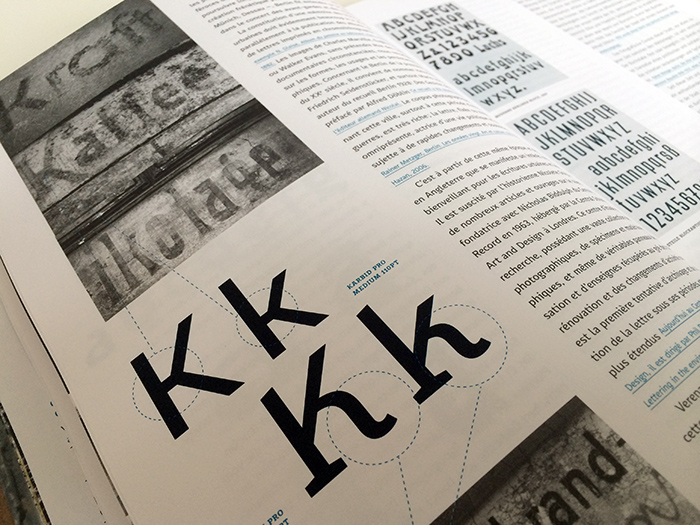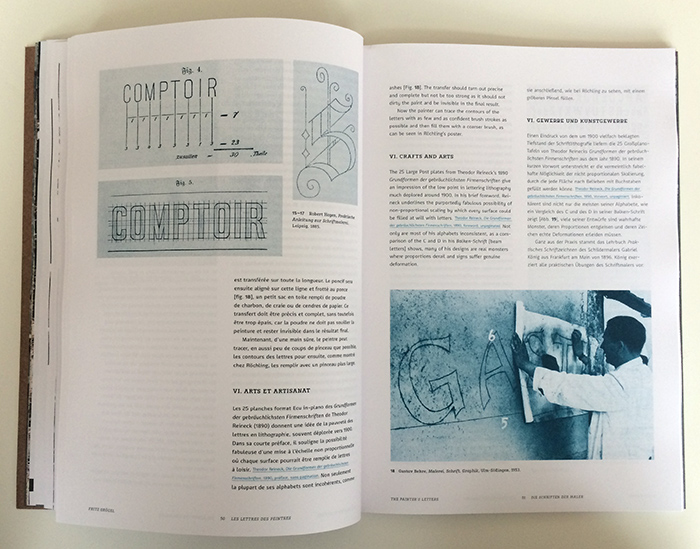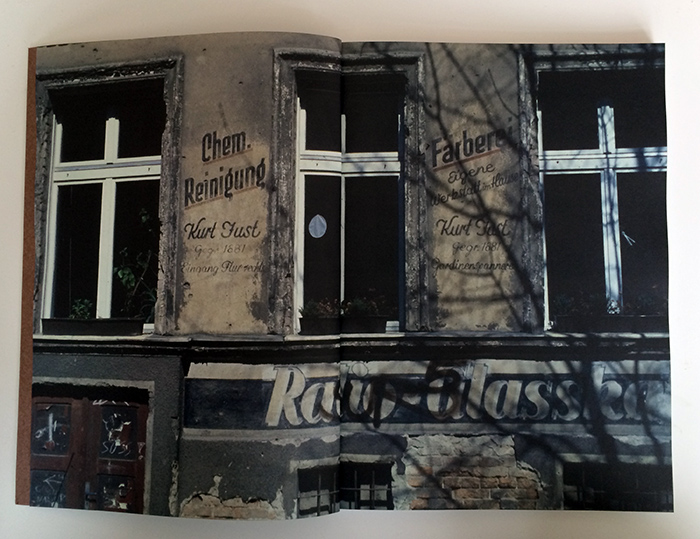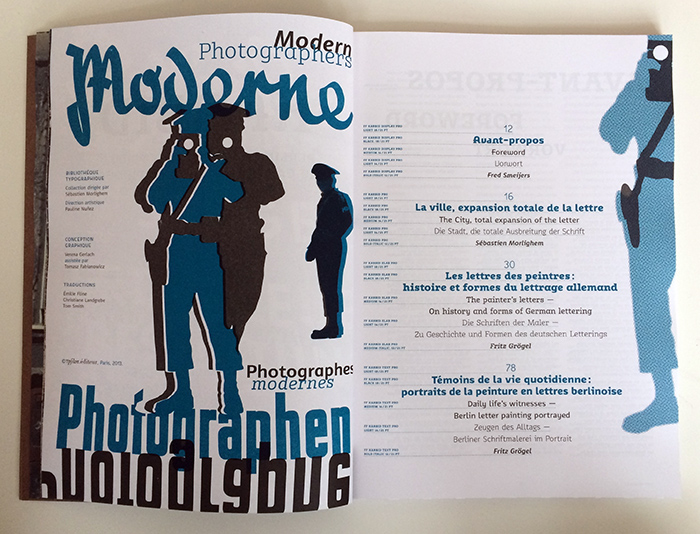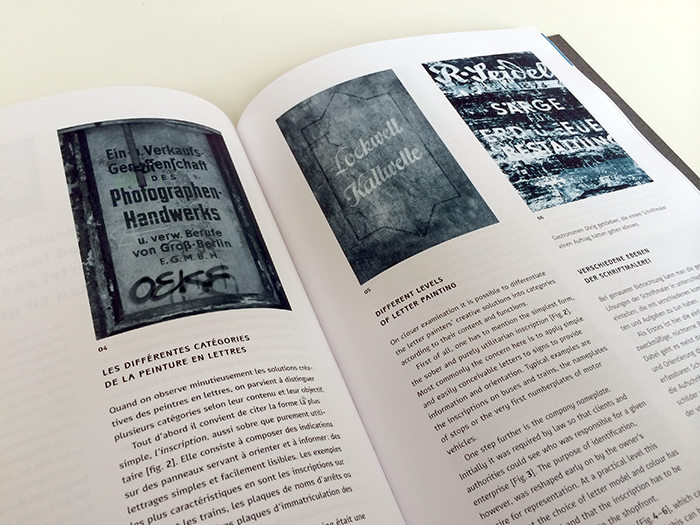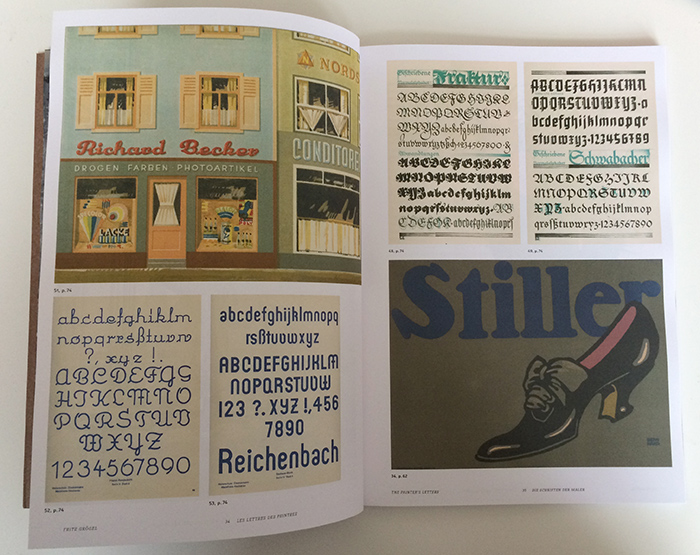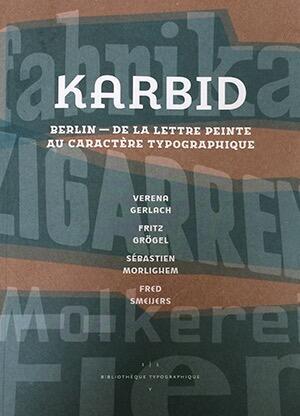
In den 1990er-Jahren durchstreifte Verena Gerlach den Nordosten Berlins zwischen Hackeschem Markt und ihrer damaligen Hochschule, der KHB in Weißensee und hielt dabei die zahlreichen erhaltenen Schriftmalereien fotografisch fest. Viele waren bereits vor dem 2. Weltkrieg entstanden und hatten im Ostteil der Stadt bis in den 1990er-Jahre überlebt. In der Auseinandersetzung mit diesen Inschriften entwickelte Verena Gerlach schließlich die Schrift FF Karbid.
Der Name Karbin stand auch für das hier vorliegende Buch Pate. Darin werden sowohl die Schrift präsentiert als auch Verena Gerlachs »Buchstabenportraits« ausgebreitet, deren dokumentarischer Wert heute um so bedeutender ist, als die Auslöschung der alten Inschriften durch Renovierungsmaßnahmen nunmehr fast gänzlich abgeschlossen ist. Die Serie von Vorher-Nachher-Bilder am Ende des Buches belegt dies eindrucksvoll.
Einführende Worte gibt es zunächst von Fred Smeijers und Sébastien Marlighem. Den Hauptteil des Buches machen neben den Bildern Gerlachs die zwei Essays von Fritz Grögel aus.
- Die Schrift der Maler – Zu Geschichte und Formen des deutschen Letterings.
- Zeugen des Alltags – Berliner Schriftenmalerei im Portrait
Grögel setzt sich also sowohl mit der Geschichte der Schildermalerei im Allgemeinen auseinander, als auch spezifisch mit den diesbezüglichen Entwicklungen in Berlin. Dies ist insbesondere deshalb interessant, da die Beschriftung im öffentlichen Raum trotz ihrer Omnipräsenz im Alltag im Fachbereich der Typografie meist links liegen gelassen wird, da es hier vornehmlich um die Drucktypografie mit Satzschriften geht. Somit ist die Recherche-Arbeit Grögels umso wertvoller, da sie mit vielen interessanten historischen Details aufwarten kann, die sich in gängigen Typografie-Büchern kaum finden werden.
Das größtenteils zweifarbig gestaltete Buch ist natürlich selbst auch in FF Karbid gesetzt und fungiert somit gleichzeitig als Schriftmusterbuch für die Karbid-Schriftsippe. Genau dies bereitete mir beim Lesen jedoch auch ein bisschen Unbehagen. Einerseits ist die Karbid nicht wirklich eine perfekte Fließtext-Schrift. Ihre eigenwilligen Details, die im Sinne ihres Ursprungs in Schildermalerschriften verständlich sind, lenken im Fließtext doch noch ziemlich ab – auch wenn sie in der Unterfamilie FF Karbid Text deutlich zurückgenommen sind. Und andererseits erzeugte diese Mischung aus Schriftmusterbuch und Fachbuch auch einen gewissen inhaltlichen Konflikt zwischen dem werblichen Nutzen eines Schriftmusters und dem rein fachlichen Inhalt der Texte.
»Karbid« ist dreisprachich (deutsch, französisch und englisch) gesetzt und bei Ypsilon Éditeur erschienen. Das Buch kann direkt beim Verlag bestellt werden.
Untertitel: Berlin – de la lettre peinte au caractère typographique
Autor(en): Gerlach/Grögel/Morlighem/Smeijers
veröffentlicht: 2013
Verlag: Ypsilon éditeur
Sprache: deutsch, englisch, französisch